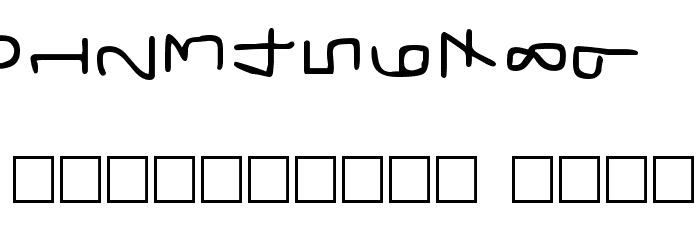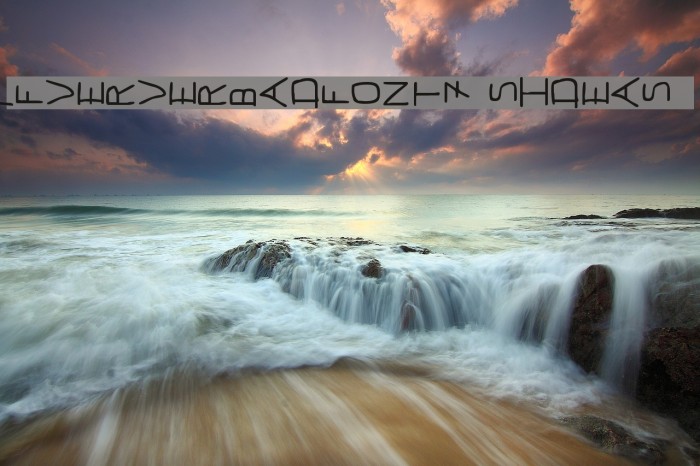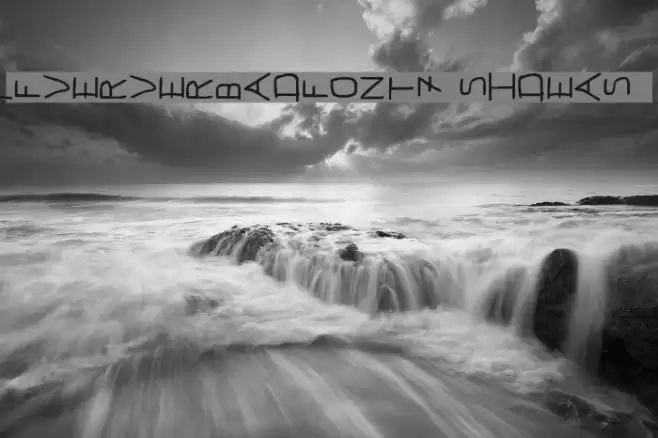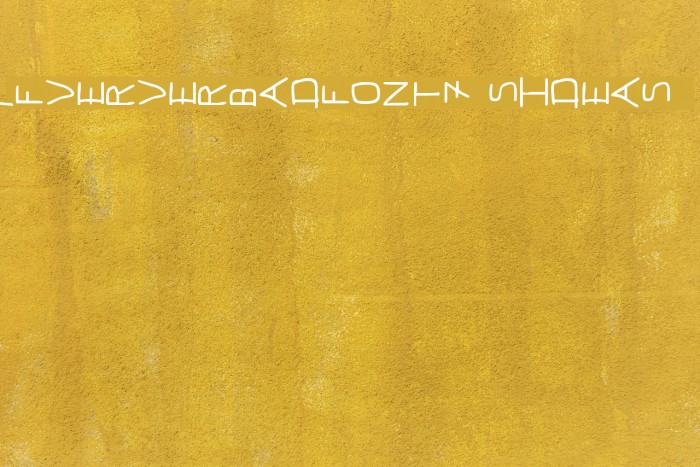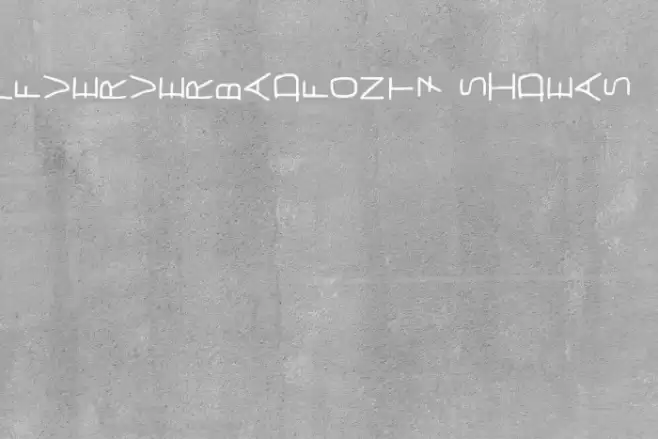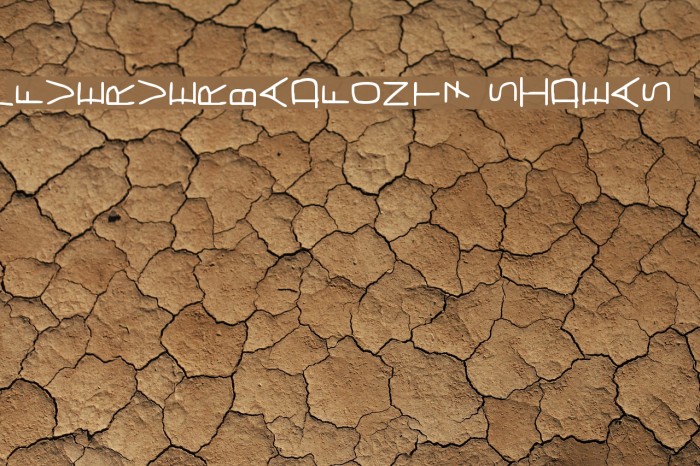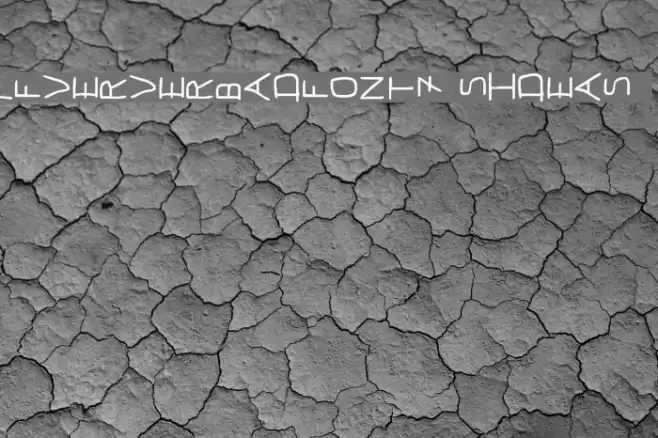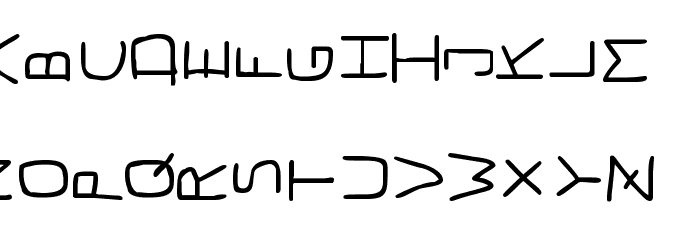
Pf_veryverybadfont7 sideways Font
| Anwendungsfall | Logos, Art projects, Creative branding |
| Vorgeschlagene Projekte | Ideal for artistic projects, modern art displays, or creative branding that seeks to capture attention with its unconventional style. |